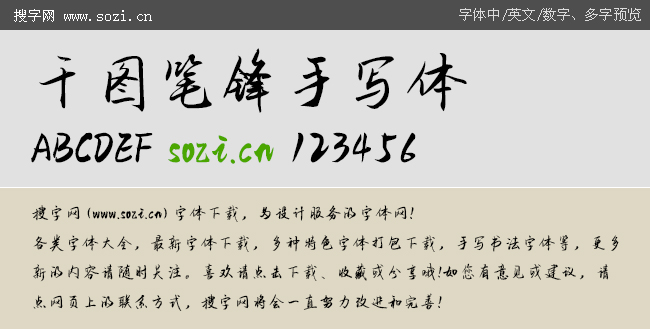
千圖筆鋒手寫體
搜字網(wǎng)給大家提供一款千圖筆鋒手寫體(非商業(yè)使用)中文字體下載,該字體是一款手寫字體,在字形筆畫上改變了平直的筆畫,用柔和的弧線將字體的柔美發(fā)揮的淋漓盡致,字形新穎獨(dú)特,簡(jiǎn)潔有力,清新淡雅,文藝范十足。整體采用連筆寫法,一氣呵成,更顯流暢。適用于海報(bào)設(shè)計(jì) 、書籍封面、包裝設(shè)計(jì)等場(chǎng)景。